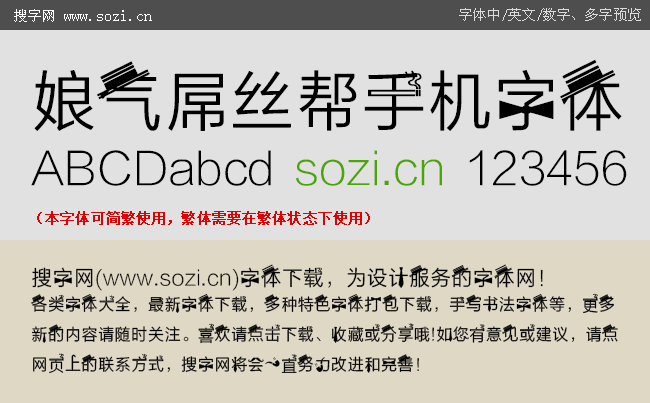
娘氣屌絲幫手機(jī)字體
搜字網(wǎng)給大家提供一款很有趣的手機(jī)中文字體下載。字體名字叫娘氣屌絲幫手機(jī)字體,這款手機(jī)字體是黑體字體為原形,為字體插入了卡通圖案。即保持了黑體易識(shí)別的風(fēng)格,又增強(qiáng)了趣味性,特別適合喜歡手機(jī)字體個(gè)性一些的朋友在手機(jī)上安裝使用。